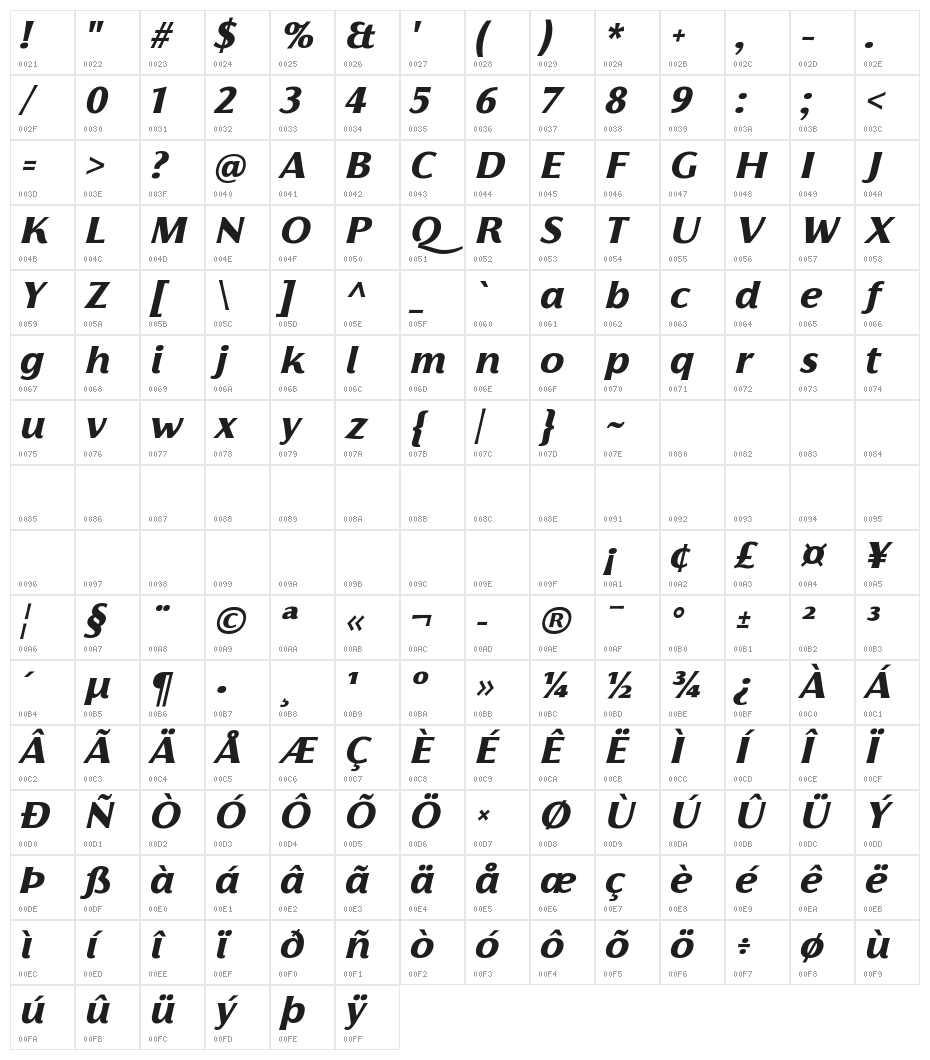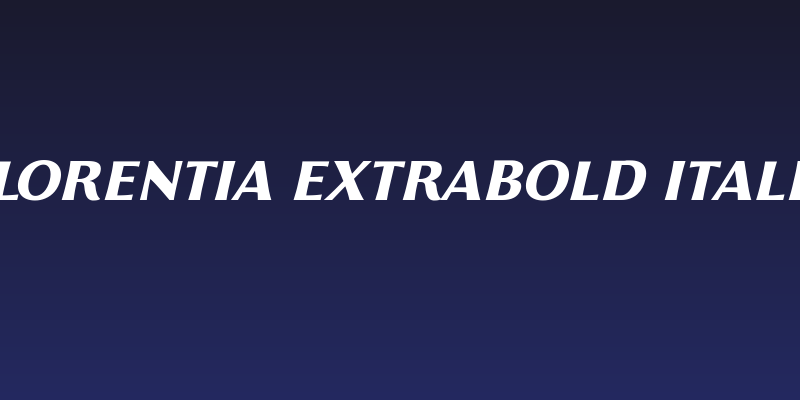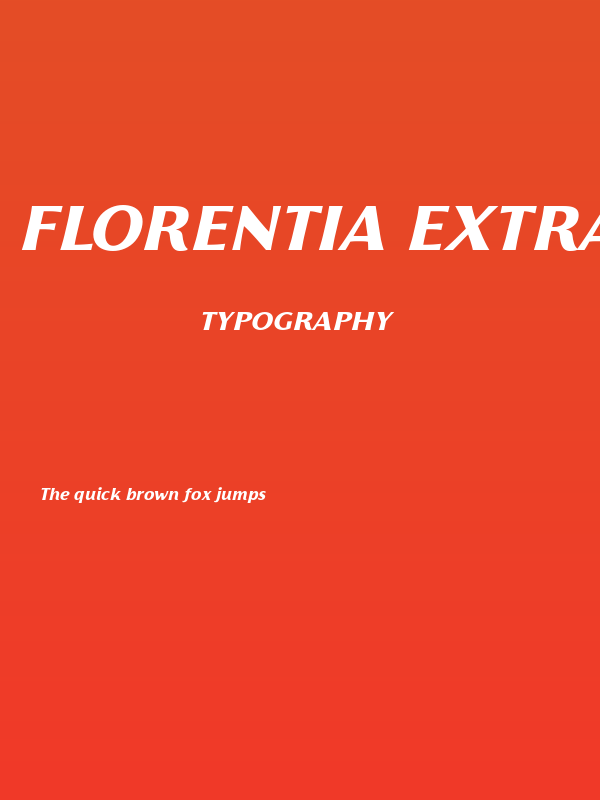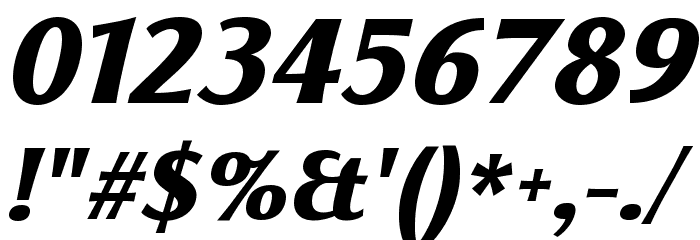
Florentia ExtraBold Italic Font
| Proyectos propuestos | Ideal for branding, advertising, and editorial design where a strong, elegant presence is needed. |